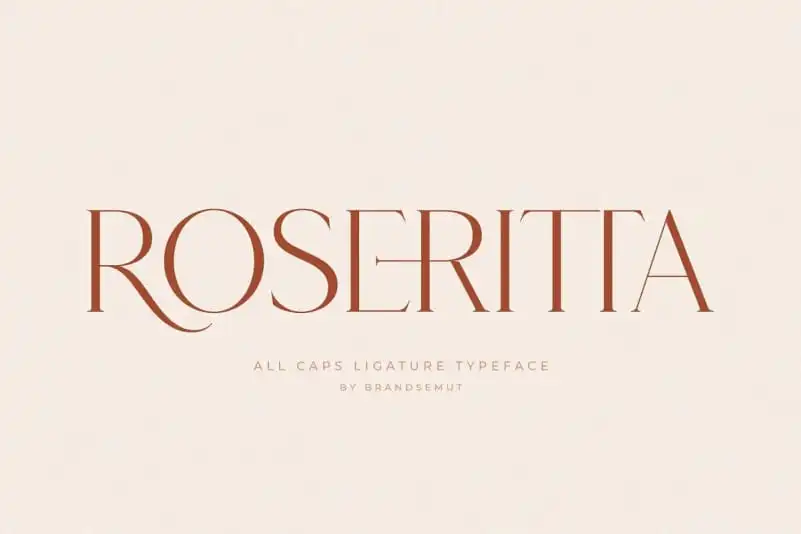
Roseritta Serif Font – Download Grátis
A Roseritta Serif Font é uma seleção única para quem valoriza estilo elegante, arte e modernidade em suas criações. Esta serif foi projetada com um toque sofisticado e artístico, ideal para projetos ambiciosos e grandiosos. Ela captura elementos tanto do passado quanto do presente, fazendo dela uma escolha ideal para logotipos, revistas e mídia social. Com seu design já pré-montado e pronta para ser usada juntos, ela se torna uma ferramenta perfeita para os designers que procuram adicionar um toque de elegância, estilo, classe e modernidade às suas criações. Seja você um designer buscando criar algo especial em seu próximo projeto ou quem deseja dar um up inovador a seus designs atuais, esta fonte se destaca como uma escolha criativa para qualquer ocasião.